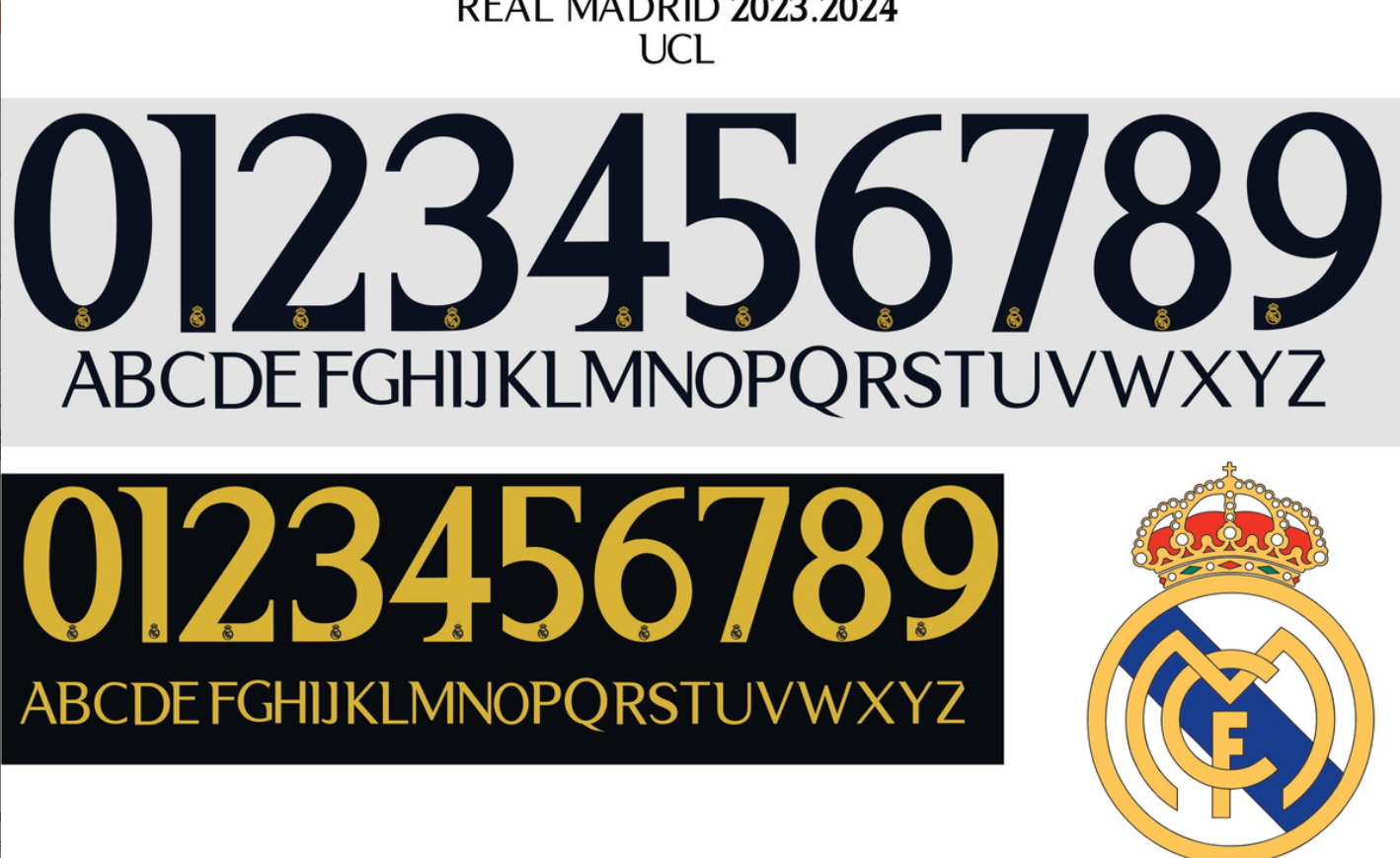
Quando falamos de realeza no futebol, falamos do Real Madrid. Para a temporada 2023/2024, a Adidas preparou um uniforme que exala elegância, e a tipografia não poderia ficar para trás.
Estilo Visual e Aplicação
A tipografia do Real Madrid para esta temporada segue uma abordagem moderna e minimalista, rompendo um pouco com o estilo retrô de anos anteriores (como o da temporada 2006). A fonte possui um peso médio (bold), com bordas levemente arredondadas e cortes estratégicos que conferem dinamismo aos números.
No uniforme titular (Home), a fonte é aplicada geralmente em preto ou dourado escuro, contrastando com o branco clássico do clube. Já no uniforme reserva (Away) e no terceiro uniforme, ela ganha variações de cor vibrantes. É importante notar que esta é a fonte “Cup/Europe”, diferente da tipografia padronizada usada na La Liga. Se o seu objetivo é recriar a magia das noites europeias, este é o arquivo correto.
Dica de Ouro: Para sublimação, lembre-se de incluir o logo do clube na base dos números (caso seu software permita essa inserção vetorial) para um acabamento 100% oficial.